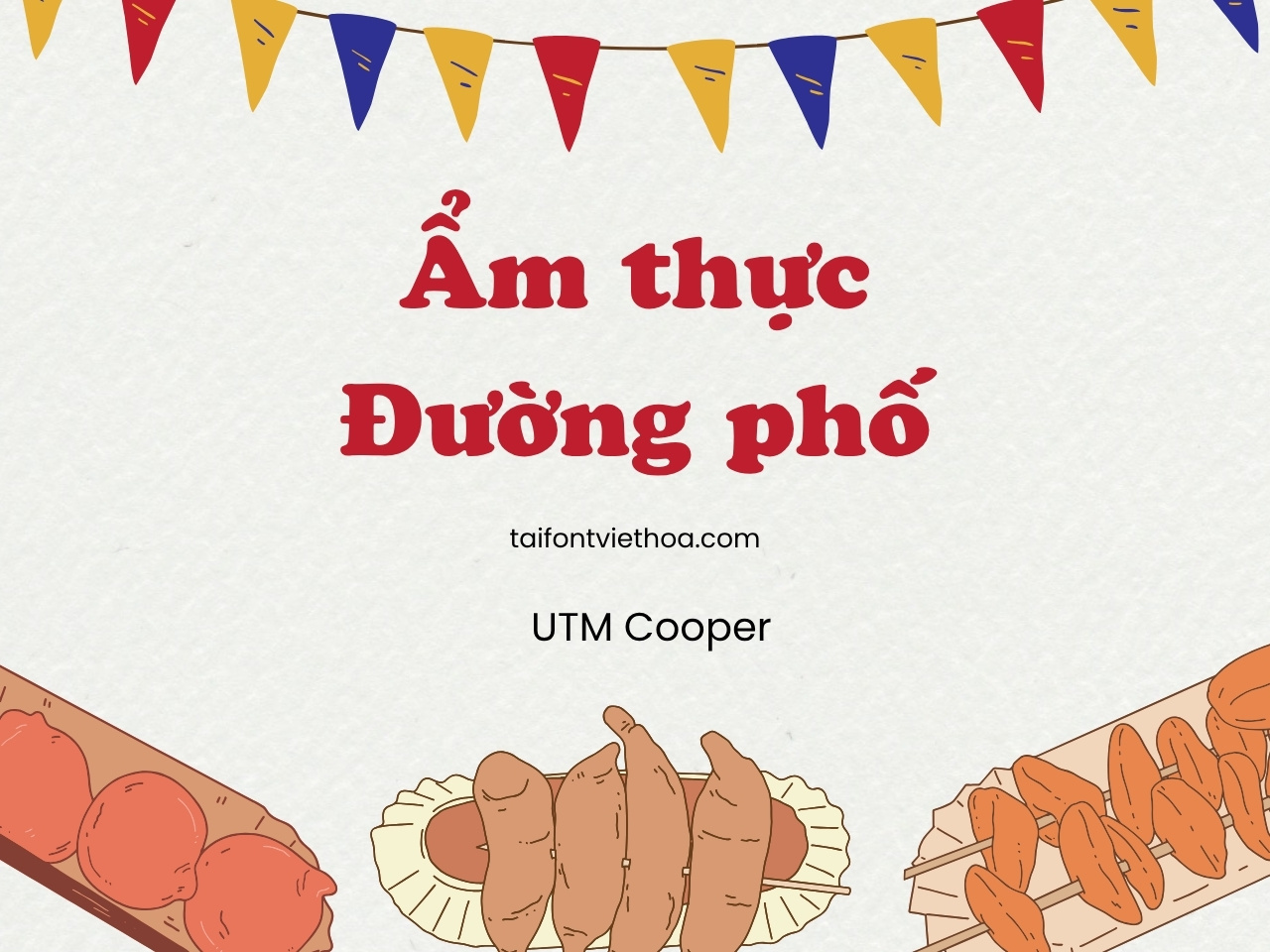
Giới thiệu về font UTM Cooper
UTM Cooper là phiên bản Việt hóa của font Cooper – một kiểu chữ serif mang phong cách cổ điển và thân thiện, được thiết kế với các nét chữ có chân (serif) tròn trịa và dày dặn, tạo cảm giác ấm áp và dễ gần. Font gốc nổi bật với thiết kế độc đáo, phù hợp cho các dự án thiết kế cần sự mềm mại và truyền thống. Phiên bản Việt hóa đã được hoàn thiện để hỗ trợ đầy đủ tiếng Việt cùng hơn 200 ngôn ngữ khác, giúp mở rộng khả năng ứng dụng trong nhiều dự án sáng tạo.
Đặc điểm thiết kế và ứng dụng của UTM Cooper
UTM Cooper sở hữu cấu trúc serif với các nét chân chữ tròn trịa, dày dặn và thiết kế cân đối, tạo cảm giác mềm mại và dễ đọc. Font phù hợp sử dụng trong thiết kế sách, tạp chí, thiệp cưới, danh thiếp và các ấn phẩm thương hiệu mang phong cách truyền thống và thân thiện. Font còn được trang bị nhiều ligature và glyph thay thế giúp tăng tính linh hoạt trong thiết kế.
Font thích hợp cho các ngành nghề như xuất bản, giáo dục, thời trang, tổ chức sự kiện và thiết kế nội thất, mang lại cảm giác ấm áp và gần gũi cho người xem.